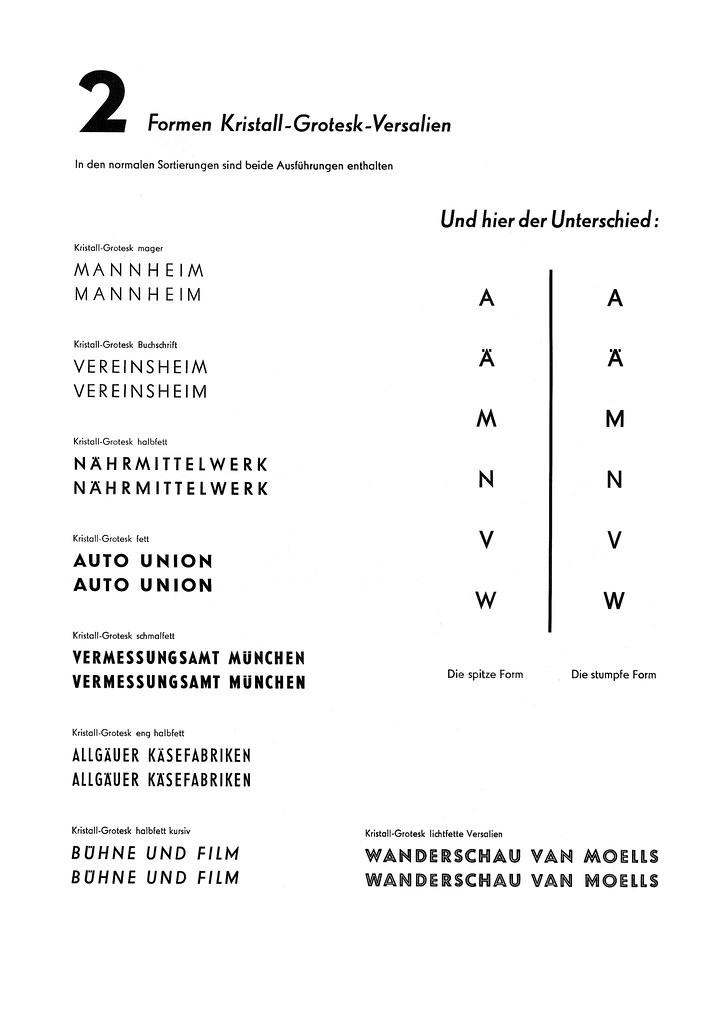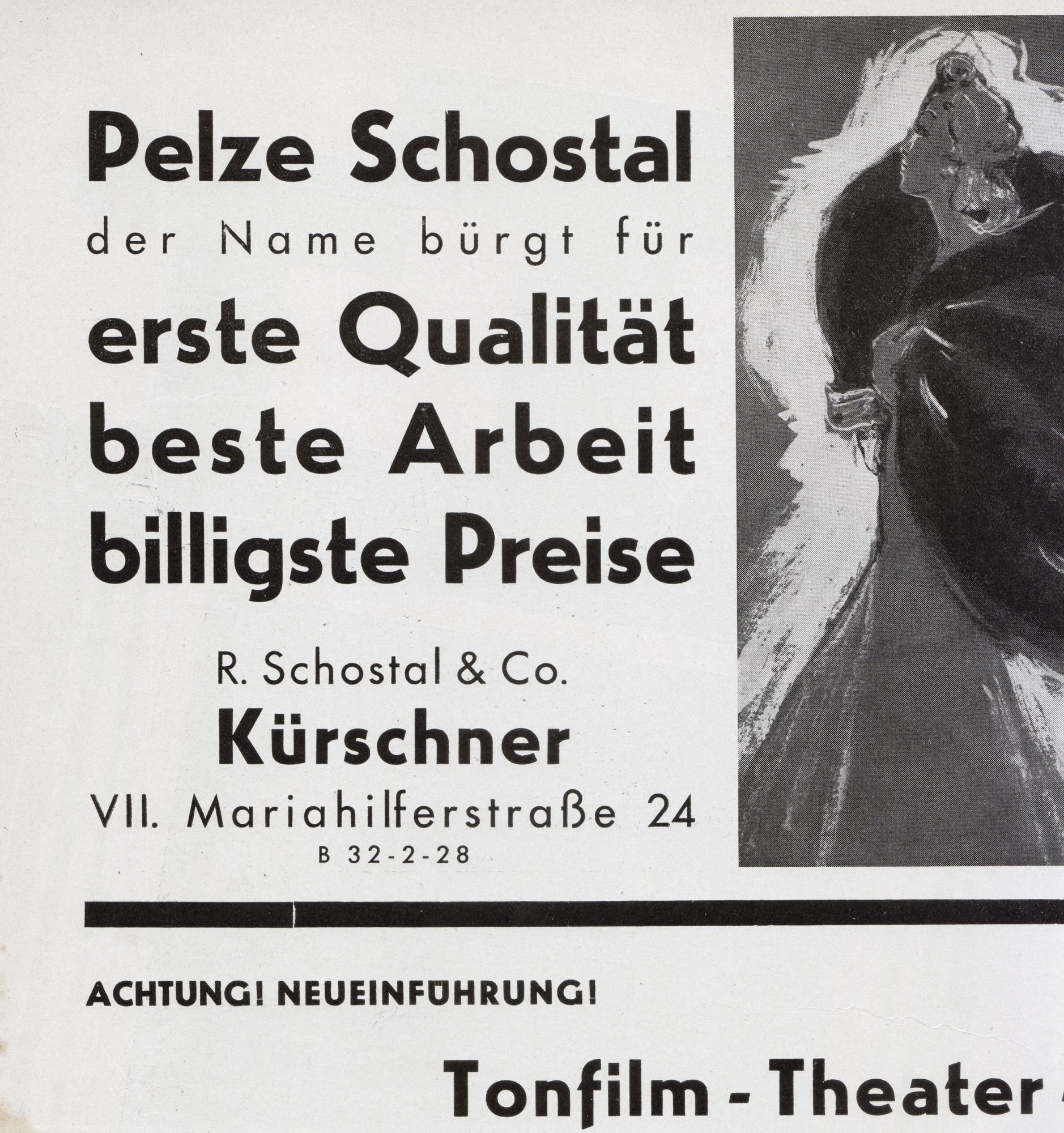
Kristall-Grotesk oder Rund-Grotesk (Tonfilm Tanz Theater Auszug Heft v. 1938)
Aus einem Heft der Reihe "Tonfilm Tanz Theater" von 1938 habe ich diese recht
großformatige Anzeige entdeckt.
Die großgeschriebenen Zeilen entstammen von der Rund-Grotesk bzw. Kristall-Grotesk.
Gibt es Unterschiede zw. Rundgrotesk und Kristallgrotesk?
Man beachte das interessante "a" mit seinem zurückgezogenen Hals und das große "G".
Gibt es diesen Fettegrad als Digitalschnitt?
Aber kauft die? Ich habe sie noch nie in heutiger Zeit angewendet gesehen.
Interessant wären die Schnitte schon.
Welche Unterschiede gibt es denn zw. "Rundgrotesk" und "Kristall-Grotesk"?